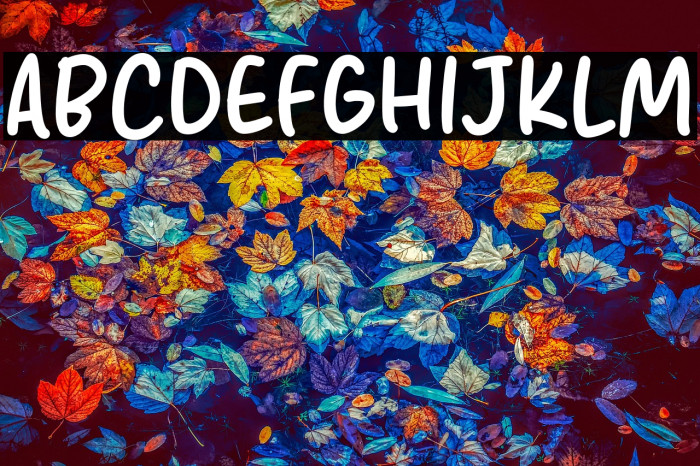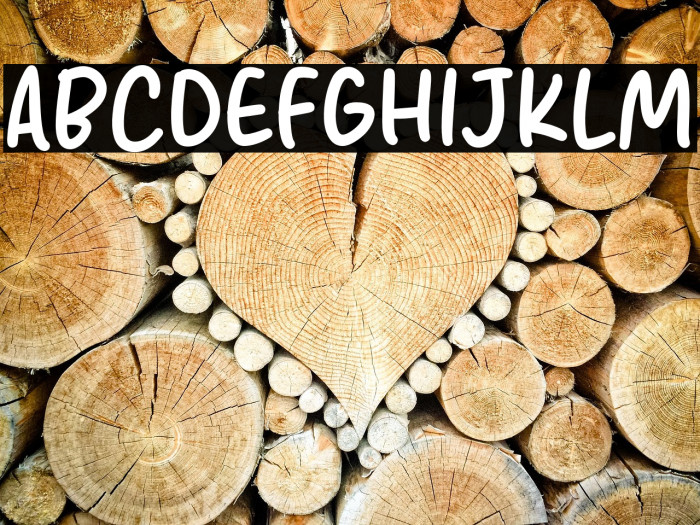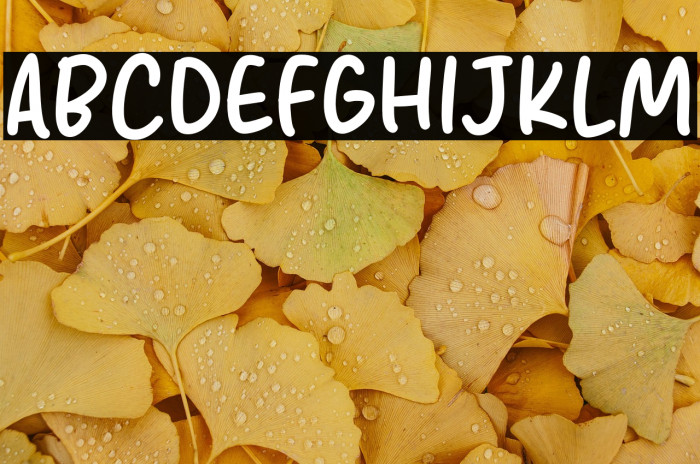
Amanda Rose Font
| Stile generale | Casual, Playful |
| Caso d'uso | Headlines, Informal text, Creative projects |
| Progetti proposti | Greeting cards, children's books, personal blogs, casual branding, and social media graphics. |